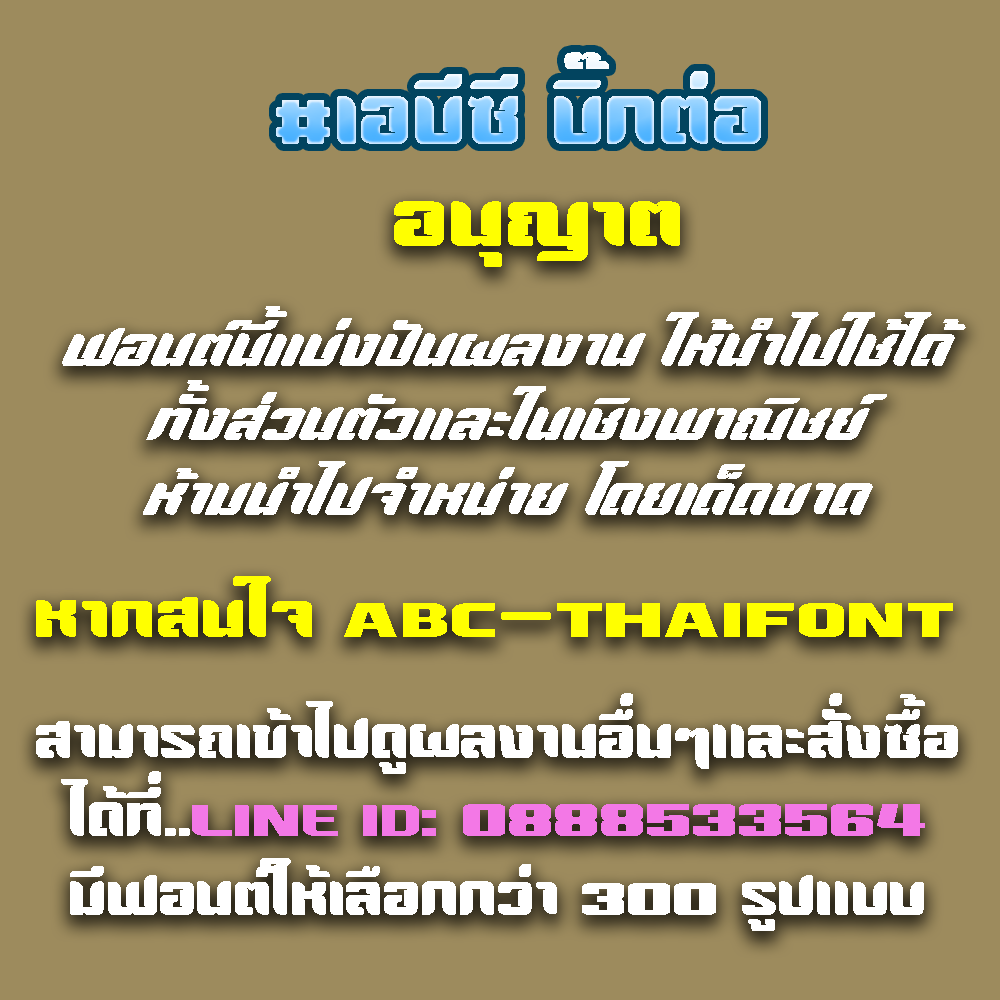
ชื่อฟอนต์ :อิกคิวซัง
ฟอนต์อิกคิวซังเป็นฟอนต์แนวน่ารัก ตัวตลก  ที่อ่านง่าย สวยงามน่ารัก ใช้ประกอบงานได้หลากหลาย แล้วแต่ช่างออกแบบจะนำไปต่อยอดออกแบบในงานได้ทั่วไป
ฟอนต์นี้เป็นผลงาน ของ : ABC-Thaifonts
สร้างสรรค์และออกแบบฟอนต์โดย: นายณภัทร  วิจิตรกรสกุล
ชื่อฟอนต์ :บิ๊กต่อ
ฟอนต์บิ๊กต่อ เป็นฟอนต์แนวฟอนต์ซิ่ง ตัวหนาๆ ตันๆ แบบบิ๊กๆ  ใช้งานตัดสติ๊กเกอร์แต่งรถ หรือพาดหัวตัวหนาๆ หรือใช้งานได้ทั่วๆไป
ฟอนต์นี้เป็นผลงาน ของ : ABC-Thaifonts
สร้างสรรค์และออกแบบฟอนต์โดย: นายณภัทร  วิจิตรกรสกุล
ชื่อฟอนต์ :ไอ้อ้วน
ฟอนต์ไอ้อ้วน เป็นฟอนต์แนวตลกน่ารัก แบบตัวหนา ใช้งานได้หลากหลายแล้วแต่จะเอาไปต่อยอด ให้ทั้งตัวตรงและตัวเอียง เอาไปใช้งานแบบไม่จำกัด
ฟอนต์นี้เป็นผลงาน ของ : ABC-Thaifonts  ก่อตั้งขึ้นเมื่อปี พ.ศ. 2561-ปัจจุบัน
สร้างสรรค์ผลงานและออกแบบฟอนต์โดย: นายณภัทร  วิจิตรกรสกุล
ชื่อฟอนต์ :เปาบุ้นจิ้น
ฟอนต์เปาบุ้นจิ้น อักษรแนวตัวเขียนภาษาจีน ที่นักออกแบบนำไปใช้ประกอบงานแนวจีน ใช้งานได้หลากหลายแล้วแต่จะเอาไปต่อยอด ให้ทั้งตัวตรงและตัวเอียง เอาไปใช้งานแบบไม่จำกัด เพื่อแบ่งปันผลงานกันชม  ขอแค่อย่าเอาไปซื้อขายก็พอคับ มันทำยาก
ฟอนต์นี้เป็นผลงาน ของ : ABC-Thaifonts  ก่อตั้งขึ้นเมื่อปี พ.ศ. 2561-ปัจจุบัน